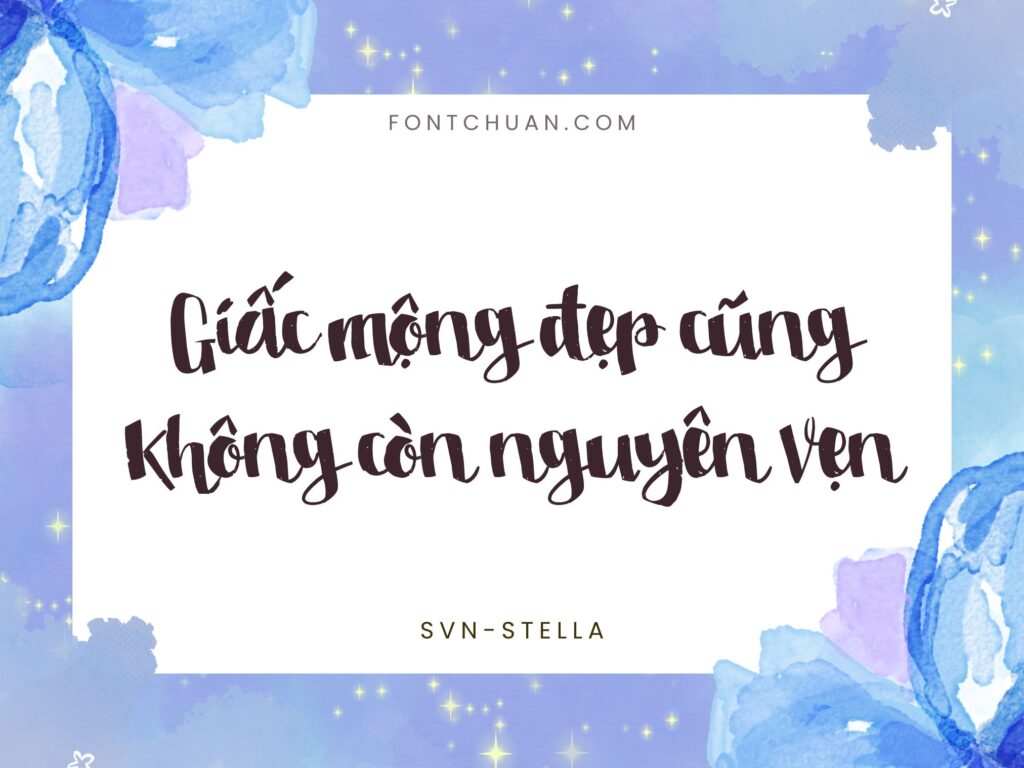
Font SVN Stella Việt Hóa
Tác giả Font: Olex Studio
Font SVN Stella là phiên bản Việt hóa của kiểu chữ Stella, được thực hiện bởi STYLEno.1 Fonts. Stella là một Font Decorative viết tay độc đáo và hiện đại, mang phong cách thân thiện và dễ thương. Font này nổi bật với các ký tự đậm, nét chữ dày dặn và độ tương phản cao, tạo nên sự thu hút và ấn tượng trong thiết kế. Stella bao gồm đầy đủ các ký tự chữ hoa, chữ thường, chữ số và các ký tự đặc biệt, hỗ trợ đa ngôn ngữ, phù hợp cho nhiều mục đích sử dụng khác nhau như thiết kế thiệp mời, tiêu đề, logo và các ấn phẩm truyền thông.
SVN Stella lý tưởng cho các dự án thiết kế yêu cầu sự thân thiện và vui nhộn, như thiệp mời, logo, tiêu đề và các ấn phẩm truyền thông. Các ngành nghề như giáo dục, ẩm thực và spa có thể tận dụng font này để tạo điểm nhấn trong thiết kế. Ngoài ra, font cũng thích hợp cho các sự kiện như Tết, Sinh nhật, Trung thu và các lễ hội khác.